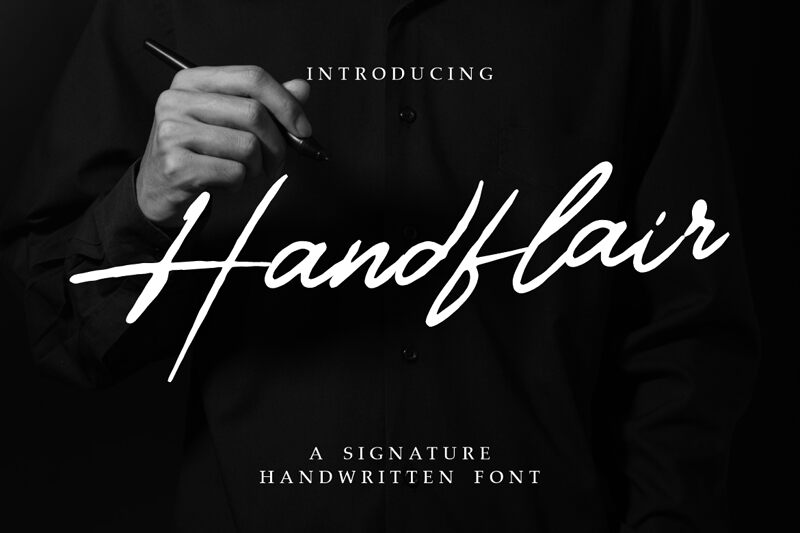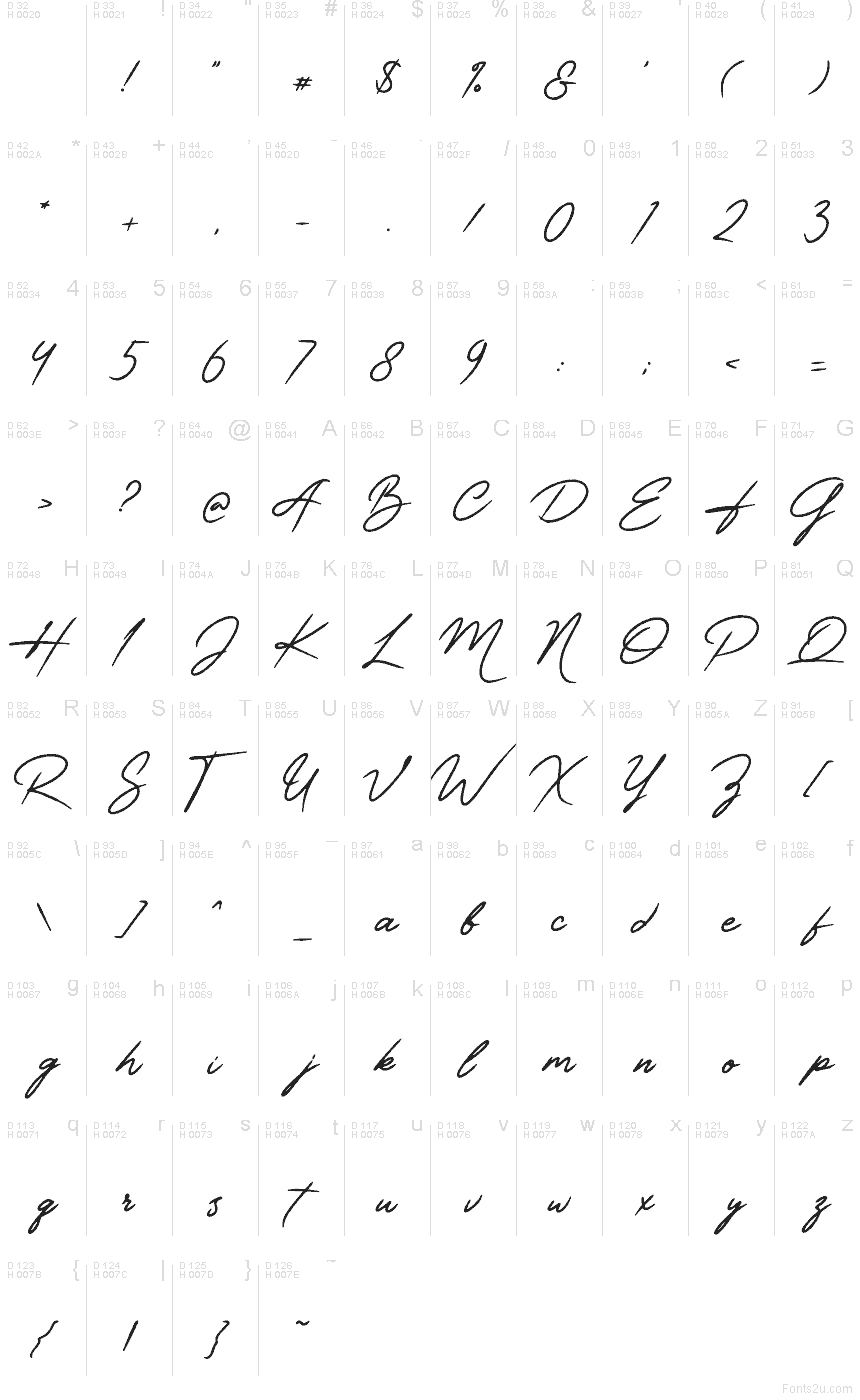
Handflair par Shanaf Studio est une police manuscrite gratuite qui capture la fluidité et le dynamisme d'une signature moderne. Grâce à ses longs tracés croisés et ses lignes effilées, cette police offre un rendu léger et personnel, loin de la rigidité formelle.
Elle est idéale pour le branding, le packaging haut de gamme, les visuels de réseaux sociaux, les invitations et les titres où un texte court a besoin de cette touche authentique. Étant une police gratuite, Handflair fonctionne également à merveille pour les ébauches de logos, les monogrammes et les titres, car ses tracés étendus confèrent une silhouette fluide aux mots les plus courts.